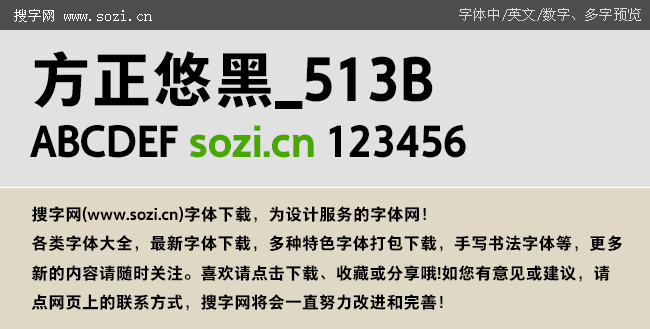
方正悠黑_513B
搜字網(wǎng)提供一款方正悠黑_513B中文字體下載,方正悠黑簡(jiǎn)體是一款端正的黑體字體,字體結(jié)構(gòu)端正均勻,清秀美觀,整體效果非常出色,可用于藝術(shù)設(shè)計(jì)、包裝印刷、簽名設(shè)計(jì)、圖形設(shè)計(jì)等領(lǐng)域。
- 風(fēng)格類(lèi)別: 黑體